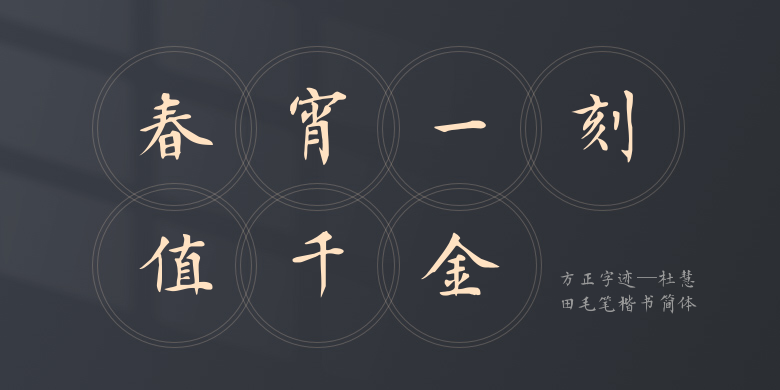
方正字迹—杜慧田毛笔楷书简体
方正字迹—杜慧田毛笔楷书简体,这款字体结构工整、笔画清晰,兼顾美观与易读性,适用于标题、正文、海报、包装、LOGO 等多种场景。字形优雅稳定,风格百搭耐看,适配日常排版与创意设计,让文字呈现更舒适、更具质感。方正字迹—杜慧田毛笔楷书简体一笔一画,皆是细节,以均衡的比例、流畅的线条打造舒适视觉体验,字形端正大气,风格简约现代。无论是商业设计、品牌宣传还是日常排版,都能轻松驾驭,让文字更有格调与力量。方正字迹—杜慧田毛笔楷书简体字体下载。